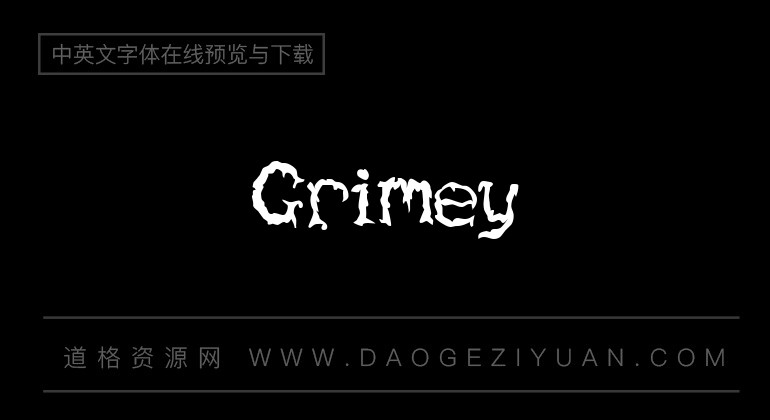
Grimey 字体是一种自由字体,也称为 Grime Art 字体,具有独特的手写风格。它在设计上融合了涂鸦、涂鸦艺术和街头文化的元素,具有强烈的视觉效果和不羁的气息。 Grimey 字体具有浓重的笔画,字母之间的间距很小,通常使用深色的颜色和白色的边框或描边来突出显示。这使得它在海报、广告、标志等设计中非常引人注目。由于其具有强烈的表现力和独特的外观,Grimey 字体在街头艺术、独立音乐和时尚行业中非常受欢迎。 Grimey 字体提供了多种不同的字形和变体,包括斜体和粗体,以及具有特殊效果的版本。此外,它还支持多种语言和字符集,使其成为一个非常多功能的字体。内容介绍
Grimey是一款非常不错的手写艺术字体,具有很好的视觉感,适合于文化类的宣传设计、商业类品牌的广告和产品包装设计以及个性化文字排版等较多场景。